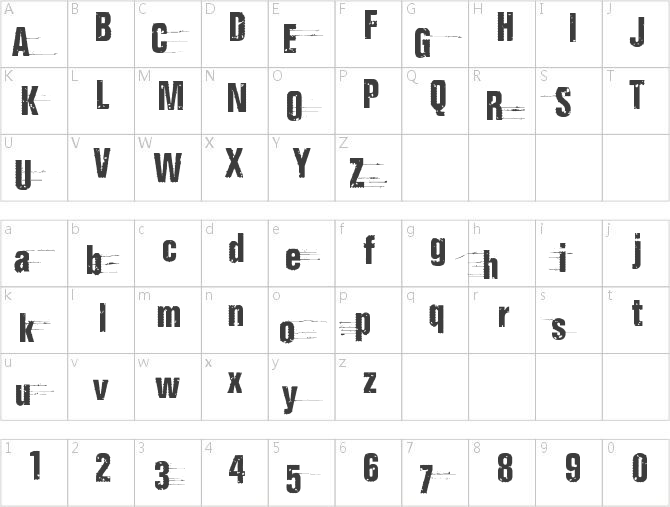
Completely Nonsense
Completely Nonsense介紹
Completely Nonsense字體字庫是一款讓人賞心悅目、百看不厭的英文字體,適合各類廣告和產(chǎn)品包裝設(shè)計(jì)應(yīng)用,字體大小0.12MB,格式為ttf字體,上傳用戶是董志高,作者/版權(quán)方為未知